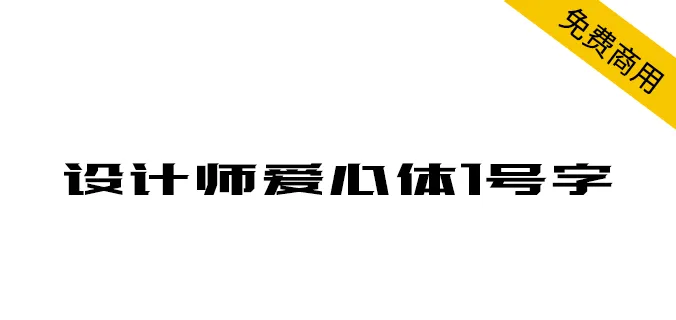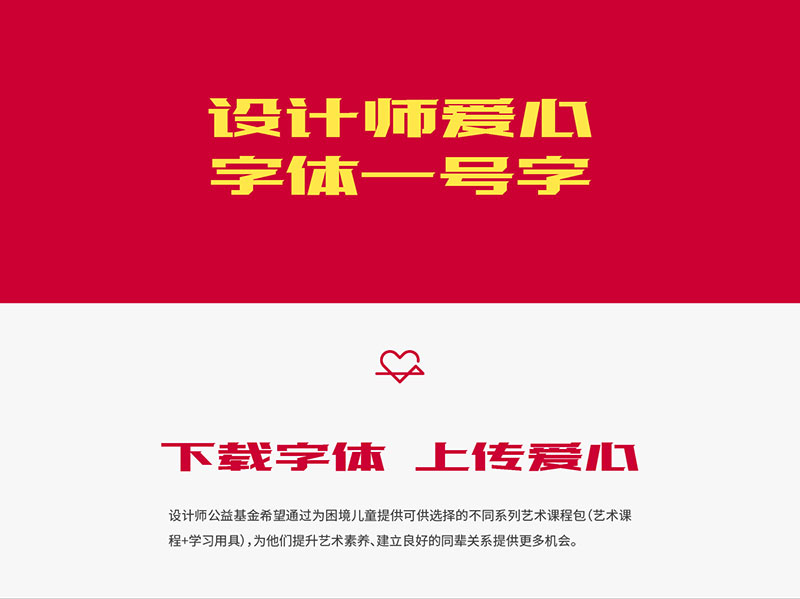
《設計師愛心體1號字》是為了能夠更好地服務困境兒童,讓他們的未來有更多的可能性,彌補他們學習生活中藝術教育的缺失,字體設計師劉兵克與歷下區未成年人救助保護中心合作,為歷下區困境兒童設立設計師公益基金,於2021年6月發佈。
設計師愛心體,源自“困境兒童”公益活動。由設計師劉兵克發起這個項目,並設計最初的字形規範及基本部首,最終,一套好用且免費的中文字體“設計師愛心體1號字”誕生,並在2021年6月發佈。
在未來的日子裡,劉兵克將會帶領他的團隊持續開發多套字庫作品,設計師愛心體1號字只是開始,未來會出現設計師愛心體2號字、3號字、4號字、5號字……而每一套愛心字庫,將會幫助和捐助予不同的受助對象。
“設計師愛心字庫,一方面可以讓設計師有更多的字庫選擇,另一方面,也讓大家通過對愛心字庫的捐助與下載,為公益事業獻上愛心,這是一件美好和溫暖的事情。我非常期待1號字能夠得到大家的認可,說實話,也更期待1號字能完成目標捐款金額。如果能夠順利完成,這會給我們帶來更大的勇氣和信心,愛心字庫這份事業,我們會更有勁頭的做下去!”
設計師愛心體1號字設計師團隊:劉兵克、李買、劉金營、劉志明、班小許、熊偉、周登恆、高晗、符重慶、李雪萍、武瑞鑫、黃婕妮